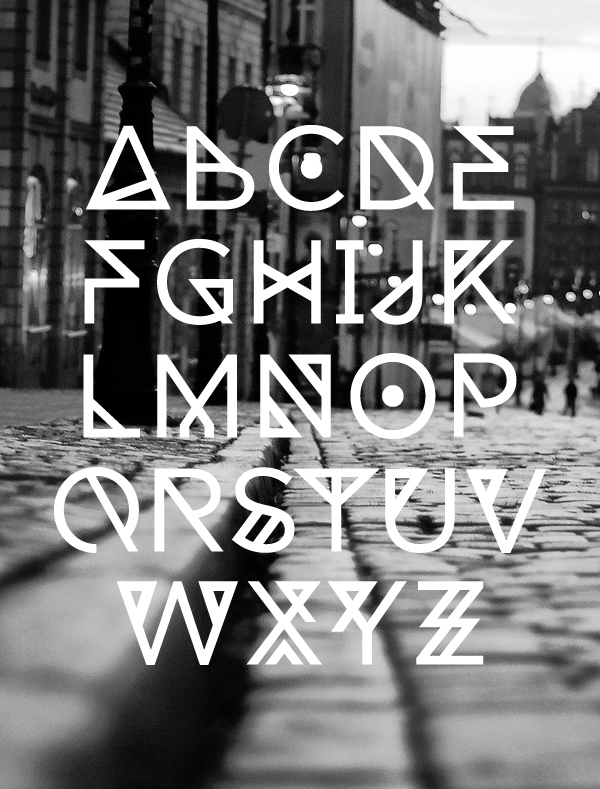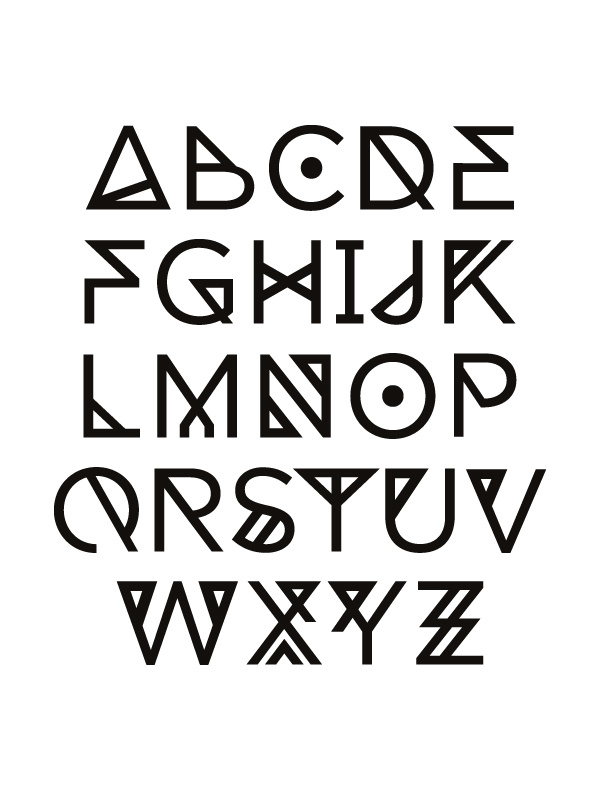
Como todos los lunes, una vez más os traemos una nueva fuente tipográfica para descargar totalmente gratis. El turno de hoy es para Dia, una fuente bastante moderna sin serifa y en mayúsculas. Gracias al diseñador noruego Tommy Larsen.